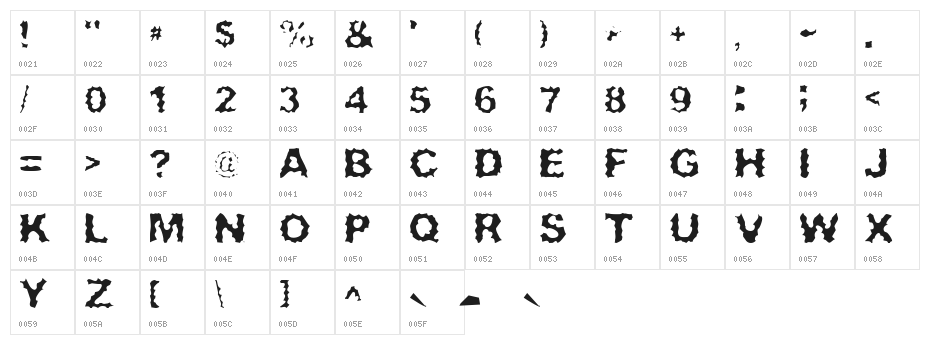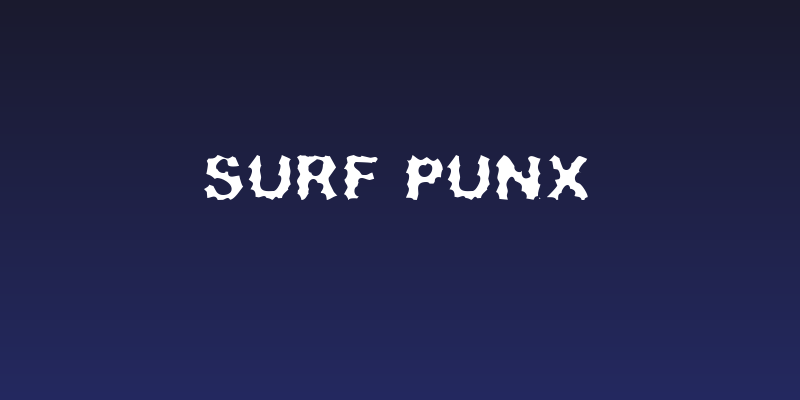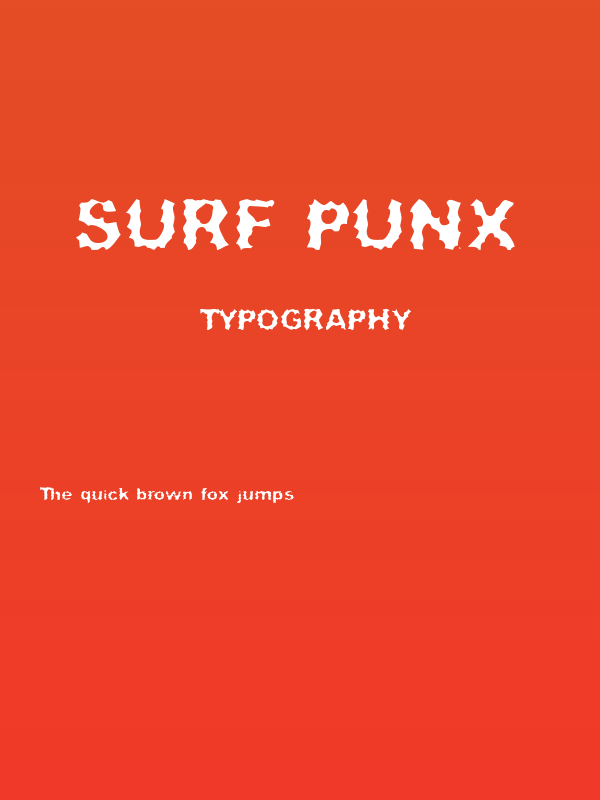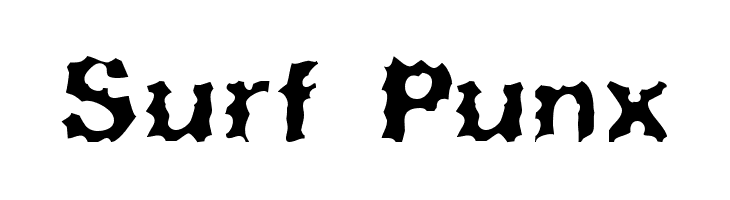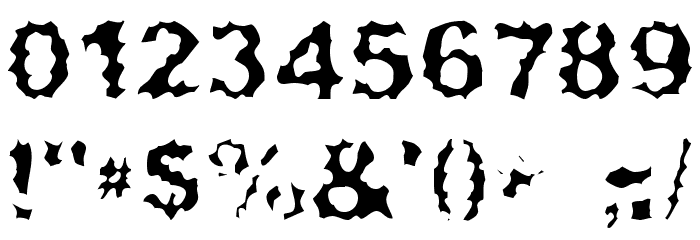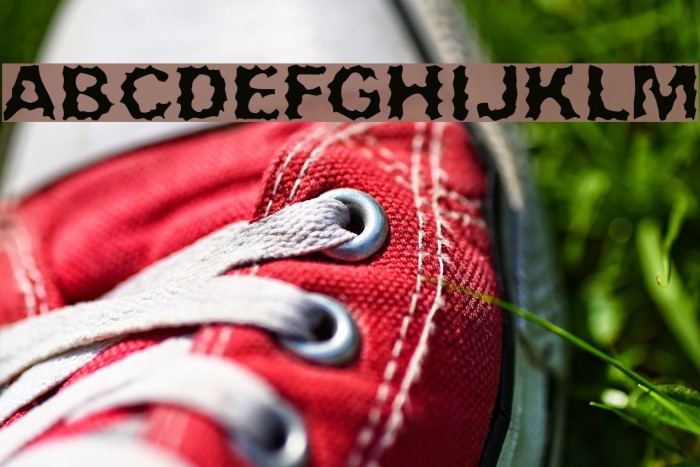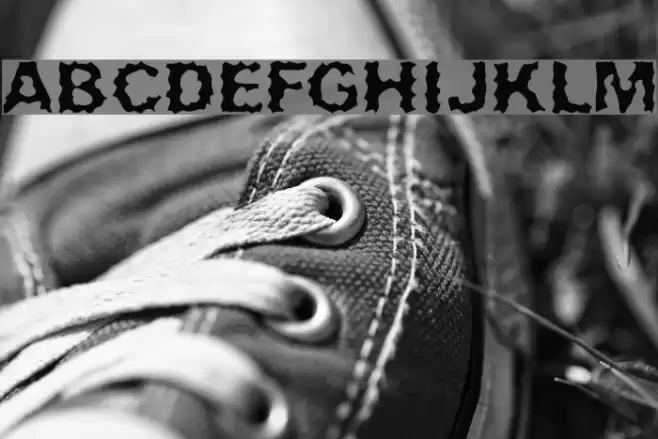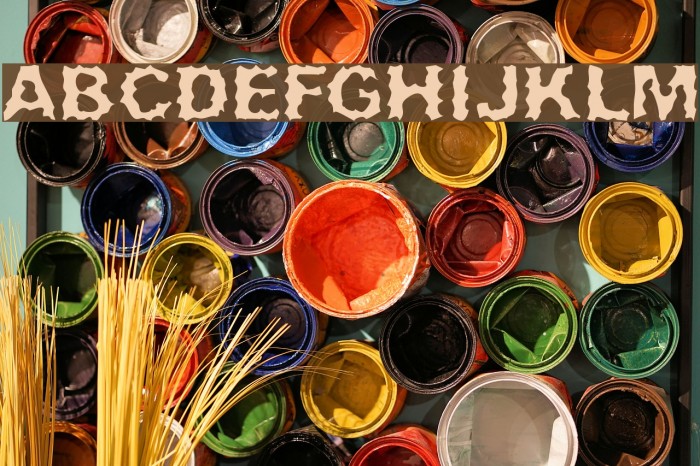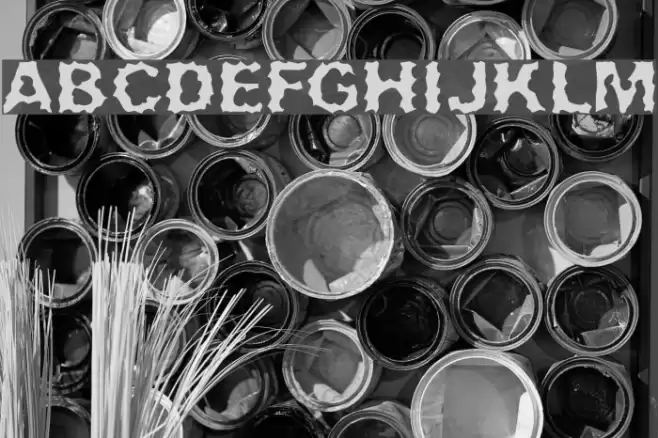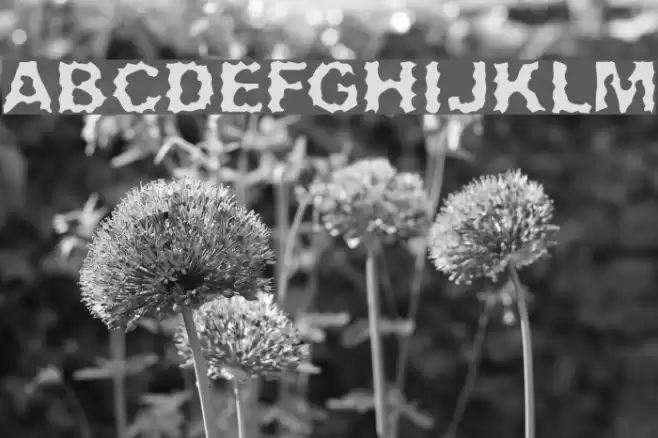
Surf Punx Font
| Stile generale | Modern, Edgy |
| Progetti proposti | Album covers, skateboarding brands, graffiti art, punk-themed posters, and edgy fashion labels. |